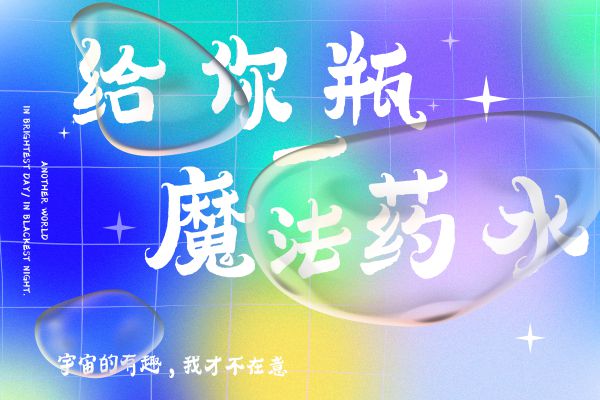
点字小胖勾
该书体为全系列手写,极大保留文字轮廓的自然与随性。字形整体圆润,在线条处理上有由粗厚入细勾,也有由细勾转粗厚,且一笔连成,保证了字形结构的流畅性和敦实感,故为“小胖勾”。 该字体给人以务实、敦厚的性格,同时也不失在丰满中略带俏皮感,其动中有静,动静结合。特别适用于标题、文案、logo等多元场景。